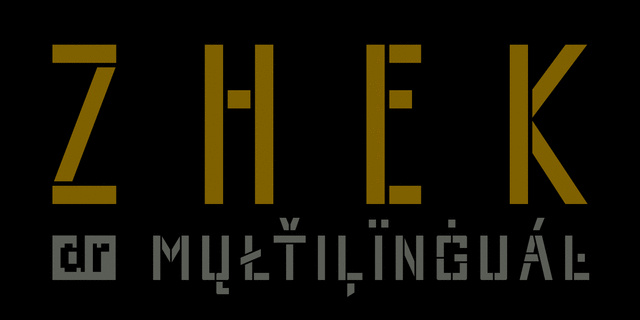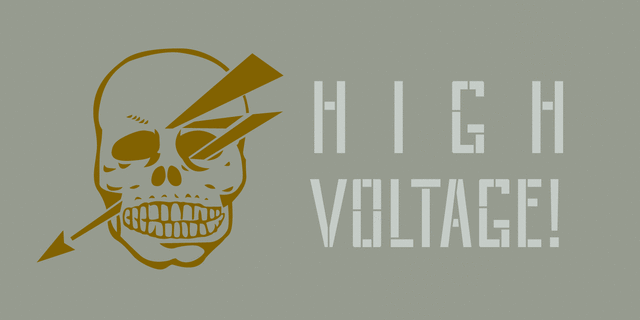
ЖЭК – это брутальный узкий трафаретный палочный шрифт. Наделен грубым обаянием рабочего класса. Отлично подходит для игр, фильмов или товаров в милитаристской и индустриальной эстетике. Шрифт разработал Дмитрий Растворцев в 2017 году.